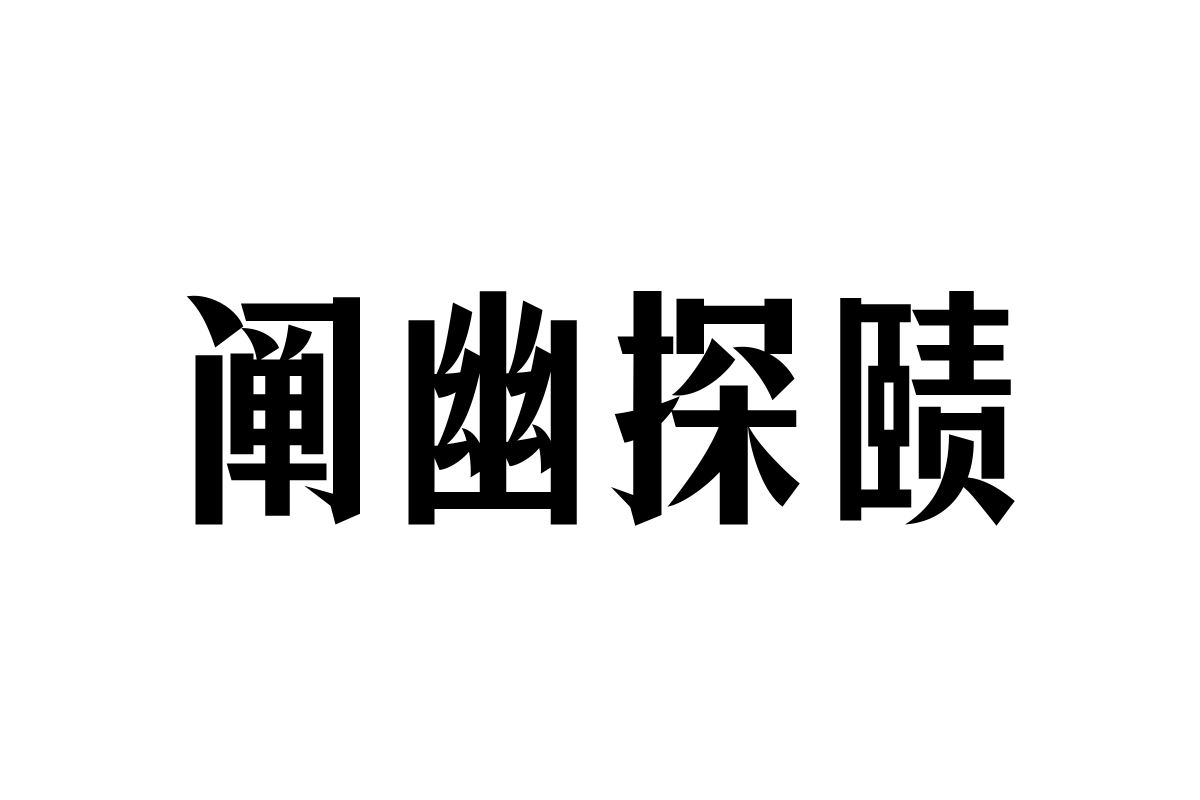
三极锐宋黑简体是一款具有超粗字体特性的中文字体,由三极锐公司设计。这款字体具有独特的设计风格和强烈的视觉冲击力,适用于需要强调文字内容的场景。
三极锐宋黑简体的特点如下:
1. 字体结构:该字体采用了传统的宋体结构,笔画粗细适中,易于阅读。同时,字体中的文字线条较为粗壮,给人一种强烈的视觉冲击感。
2. 字体风格:三极锐宋黑简体的字体风格独特,线条流畅且富有张力。它能够很好地展示出文字内容的精髓,使读者更容易理解所传达的信息。
3. 适用场景:由于其超粗的字体特性,三极锐宋黑简体特别适合用于需要强调文字内容的场景,如广告、标题、标语等。此外,该字体也适用于需要展示强烈视觉效果的场合,如海报、宣传册等。
总之,三极锐宋黑简体是一款具有超粗字体特性的中文字体,适合用于需要强调文字内容的场景。它具有独特的设计风格和强烈的视觉冲击力,能够很好地展示出文字内容的精髓。